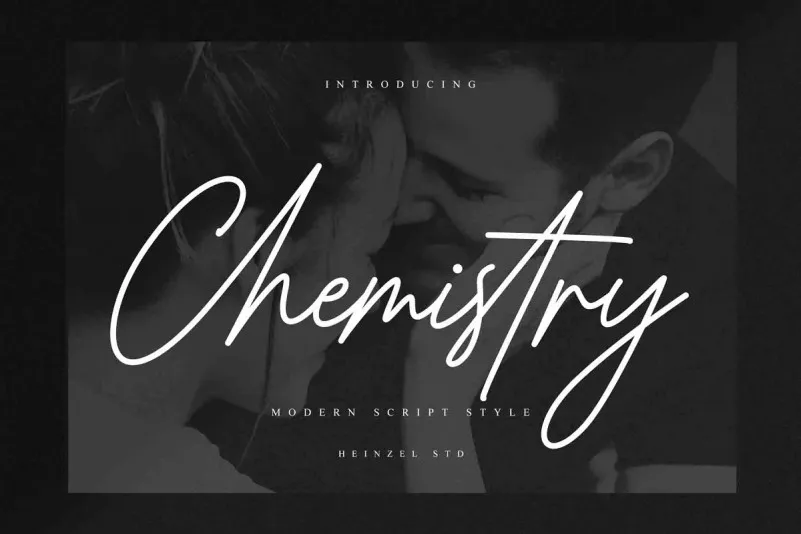
Chemistry Font – Fonte Grátis
Chemistry Font
Aqui está uma versão em português do Brasil para a descrição da fonte ‘Chemistry Font’ conforme as instruções: Esta fonte foi projetada pela Heinzel Std., uma tipografia script de escrita manuscrita com um estilo moderno. Ideal para uma variedade imensa de projetos, desde identidades visuais e materiais publicitários até cartas de aniversário e convites de casamento. Suave e versátil, esta fonte está perfeitamente equipada para dar vida a uma infinidade de ideias criativas no design editorial ou gráfico. Perfeito para logotipos, fotografias digitais, marca d’água, citações em blogs e postagens nas redes sociais. E também ideal para cabeçalhos de postais, material de festa, rótulos de moda e roupas. O design fluido desta fonte a torna uma escolha ideal para qualquer projeto que exija um toque sofisticado e elegante em seu design visual. Com ‘Chemistry Font’, você tem à sua disposição um recurso gráfico extremamente versátil, projetada para se adaptar às mais diversas necessidades de criação. Sem dúvida, uma fonte essencial para qualquer designer que procura adicionar detalhes atraentes e distintivos a seus trabalhos.